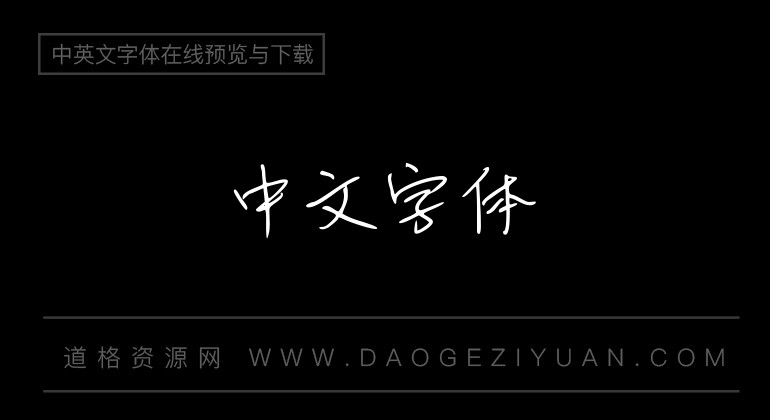
Aa小狐狸
? Aa小狐狸是一款可爱的字体,它的字体特点是具有独特的古典风格,字母采用古典曲线绘制,字体显得柔和可爱,给人以微妙的情感。它的字体风格可以被用于婚礼邀请函、节日卡片、海报等等,为您的作品增添浪漫气息。
Aa小狐狸是一款非常不错的手写艺术字体,具有很好的视觉感,适合于文化类的宣传设计、商业类品牌的广告和产品包装设计以及个性化文字排版等较多场景。
Aa小狐狸字符映射图